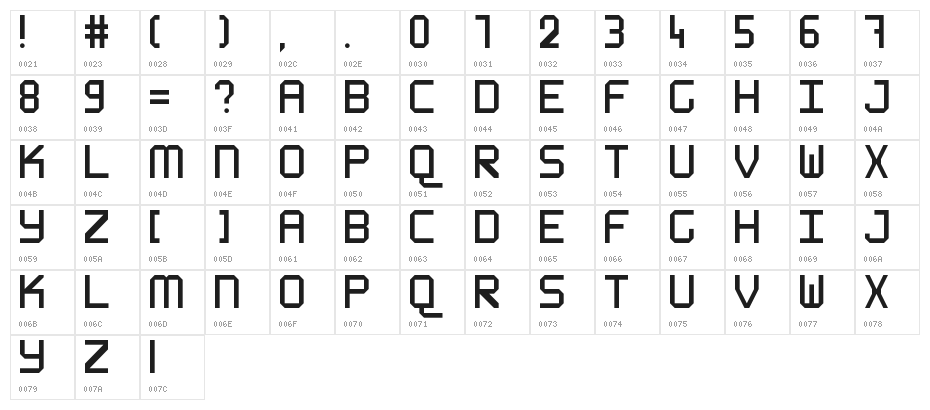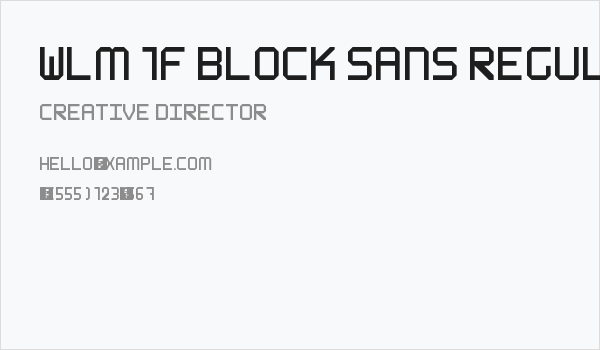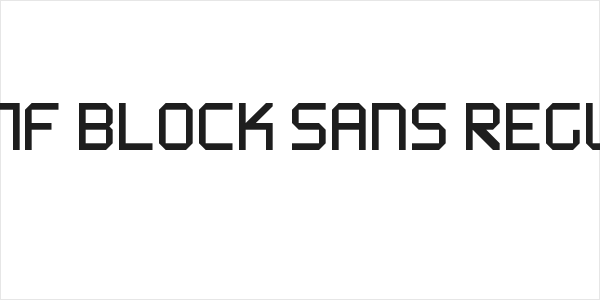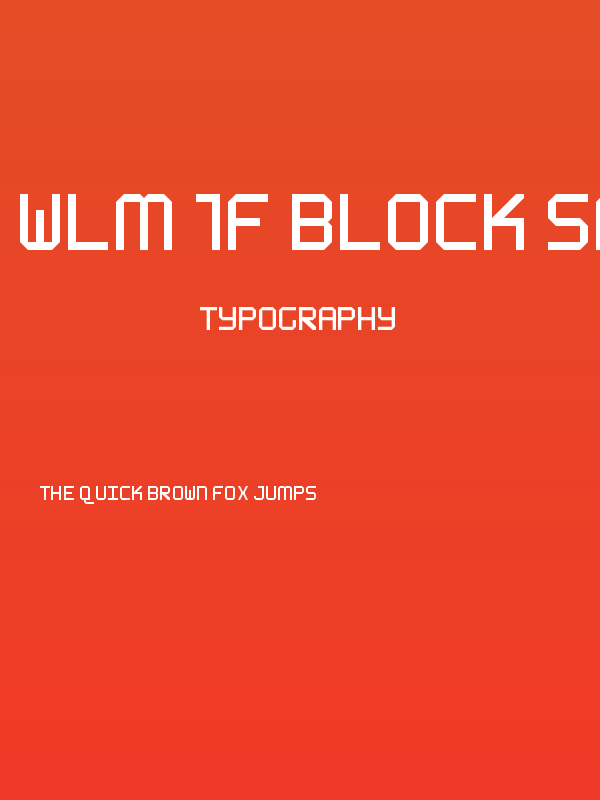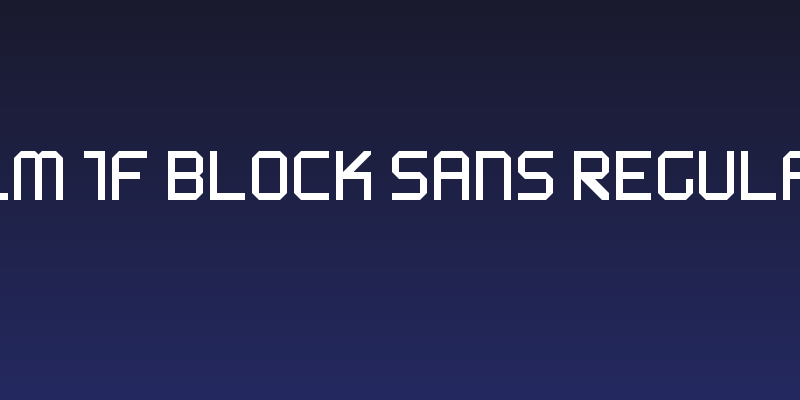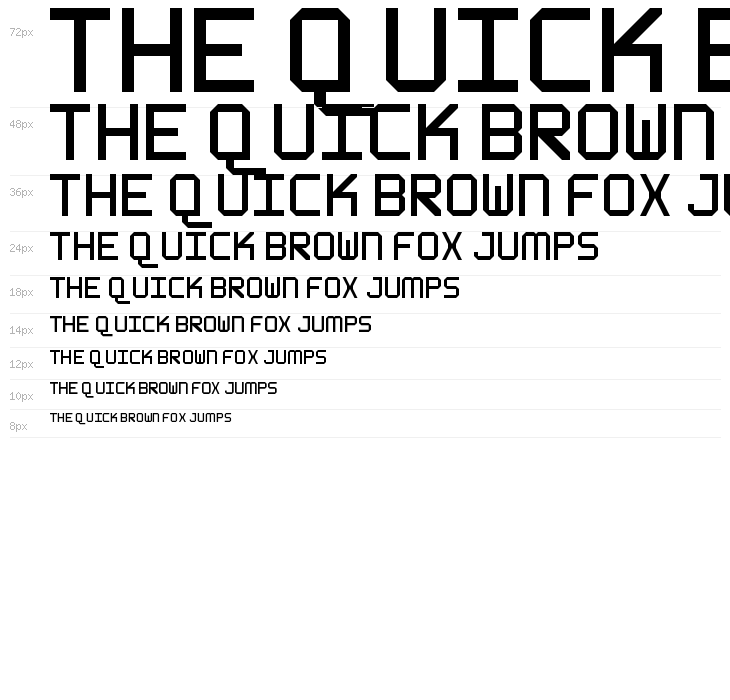
WLM 1F Block Sans Regular Font
| Progetti proposti | Ideal for branding, signage, posters, and any project needing a strong visual impact. |
WLM 1F Block Sans Regular